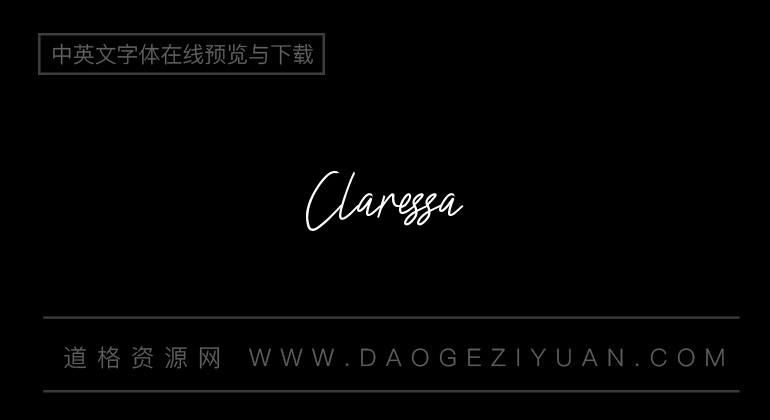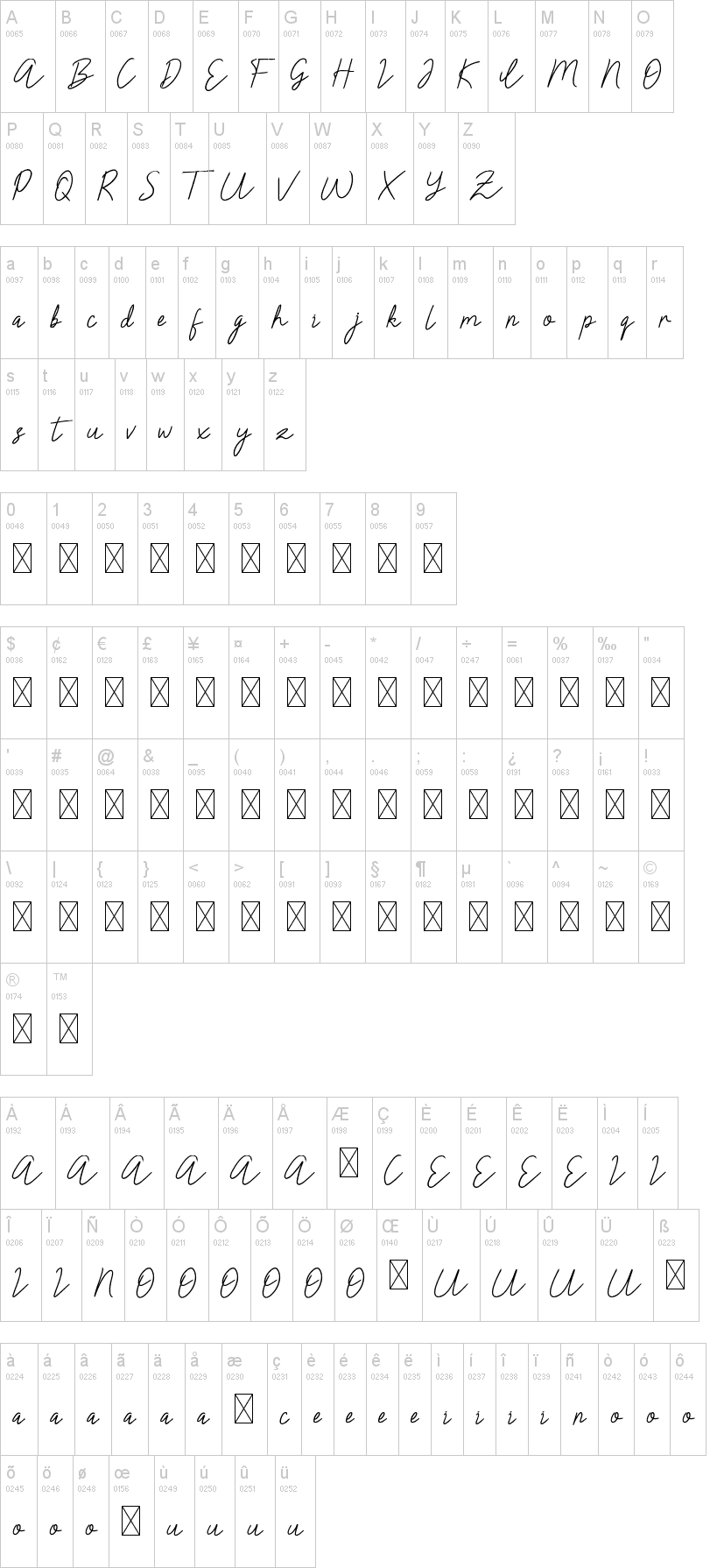
Claressa
Claressa 是一款优雅的英文字体,它采用精致的英文字体设计,具有细腻的笔画和优美的曲线,营造出温柔、灵动的气氛。它的字体特点是细节入微,给人以温柔、优雅的感觉,适合用于报纸、杂志、海报等印刷品的设计。
Claressa是一款非常不错的手写艺术字体,具有很好的视觉感,适合于文化类的宣传设计、商业类品牌的广告和产品包装设计以及个性化文字排版等较多场景。
Claressa字符映射图